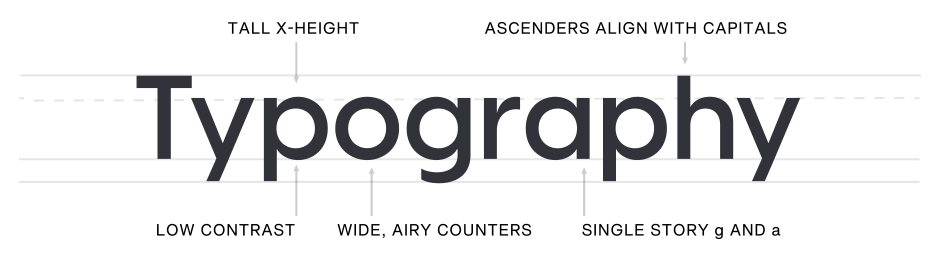
Visby CF Fuente Guía de campo
Buenas prácticas
Visby CF es versátil, y sus distintos puntos fuertes entran en juego en diferentes casos de uso. En tamaños grandes, Visby se ha utilizado para titulares y logotipos. Gracias a su diseño limpio, también se lee bien en tamaños pequeños, lo que la convierte en una opción excelente para subtítulos y pies de foto. Este doble enfoque permite que el cuerpo de texto fuente ocupe un lugar central, creando un ritmo visual de Visby en grande, un cuerpo de texto de tamaño medio y Visby de nuevo en pequeño.
Familia
Ocho pesos de diseños romanos, cada uno con un oblicuo complementario, para un total de 16 estilos.
Fuente Hechos
- Visby se inspira en el mal humor de una fría noche ártica o nórdica combinada con la calidez y la alegría del fuego.
- Visby incluye un amplio soporte de idiomas, incluidos los alfabetos latino y cirílico. Cubre muchos idiomas, desde el vietnamita hasta el ucraniano, y se están añadiendo más funciones, como el alfabeto fonético internacional.
Raíces
Visby CF es uno de los primeros tipos de letra de Connary Fagen, con muchas actualizaciones a lo largo de los años que lo mantienen fresco y añaden nuevas características. La motivación que impulsó el diseño de Visby fue la búsqueda de un aspecto aéreo y geométrico que no escatimara en personalidad. Elementos como el rabito corto de la g minúscula y la simpática "sobremordida" de la e minúscula confieren al tipo de letra una voz que va más allá de la pura simplicidad, al tiempo que se mantiene fiel al ideal minimalista básico.
Legibilidad
La construcción de Visby es abierta y aireada, con círculos básicos y líneas rectas como elementos básicos. Esto ayuda a que el tipo de letra se lea bien en casi todos los casos.
Cómo detectar el Visby CF
Opciones alternativas
Maridaje perfecto